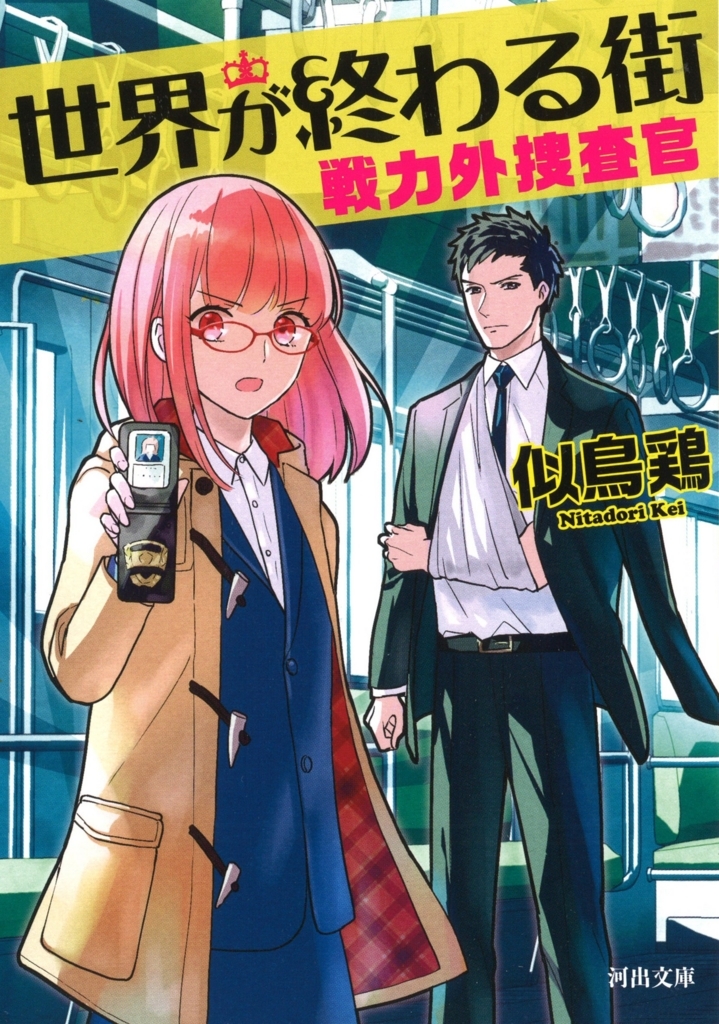
戦力外捜査官
「戦力外捜査官」は似鳥鶏氏著書による日本の推理小説のシリーズ。また、2014年1月11日から3月15日までテレビドラマとして放送された。
戦力外捜査官シリーズのタイトルのフォントにロマン雪が採用
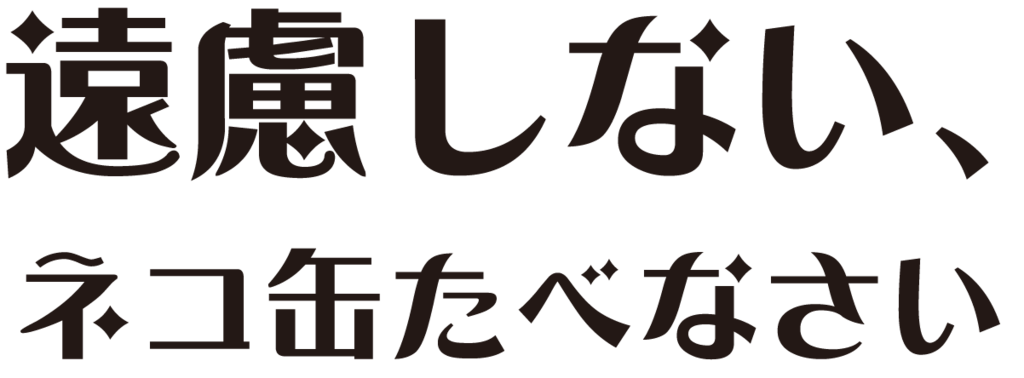
河出文庫「戦力外捜査官」シリーズのタイトルにダイナフォントのロマン雪が採用されている。
ロマン雪
1925年の藤原太一著書による『図案化せる実用文字』から着想を得て、図中の婦人の華麗な装いや愛らしいスタイルをヒントにして、大正末期から昭和初期にかけての古典ロマンの雰囲気を再現した書体。ひし形など独特の字形が大きなインパクトを与える事から、ロゴやPOPなどで大きく活用できる。